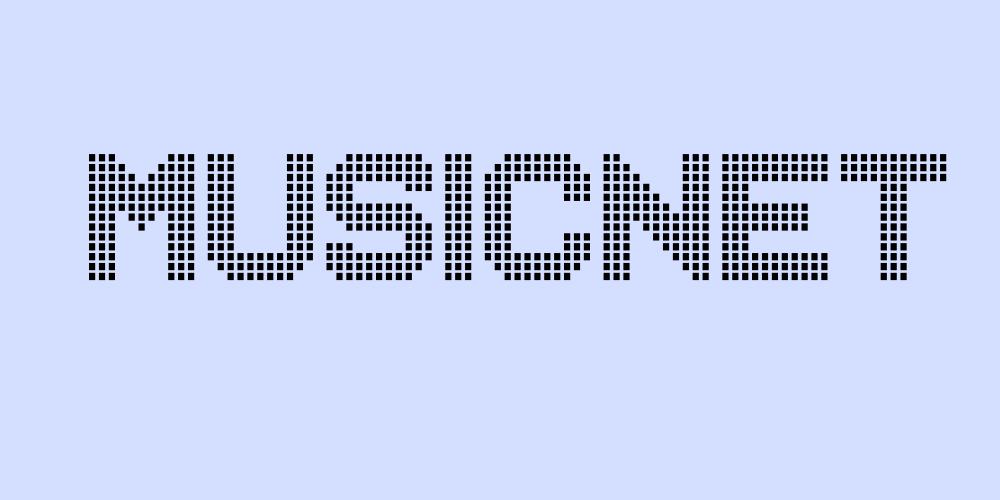
A fonte Musicnet é uma paixanteira escolha para qualquer projeto que busque entrelaçar estilo retro com modernidade pura. Desenvolvida pelo designer Hamilton, ela se destaca na categoria de Pixel Fonts por sua capacidade única de capturar o espírito nostálgico dos anos 80 e 90 ao misturá-la com um toque atual, criando um resultado vibrante e reconhecível. Com um design minimalista que valoriza cada detalhe pixelado, a Musicnet é uma font perfeita para elementos de marca, logotipos ou qualquer conteúdo digital onde você deseja destacar seu estilo. Suas linhas levemente suavizadas e texturas únicas garantem que seja perfeitamente legível sem comprometer o visual vintage que tanto valorizamos. Adicionalmente, a Musicnet foi projetada para manter uma consistência no design ao longo de sua família completa de fontes. Seja você criando um site minimalista ou trabalhando em um projeto gráfico mais elaborado, esta font oferece um conjunto vasto que torna a implementação de seu estilo pixelado ainda mais simples e harmonioso. Estamos certos de que essa font vai capturar o coração dos amantes da nostalgia digital, enquanto oferece uma solução ideal para os desafios do design moderno. Sem dúvida, Musicnet é uma escolha inteligente quando se trata de trazer um toque único à sua arte digital e em qualquer projeto visual que você esteja desenvolvendo.